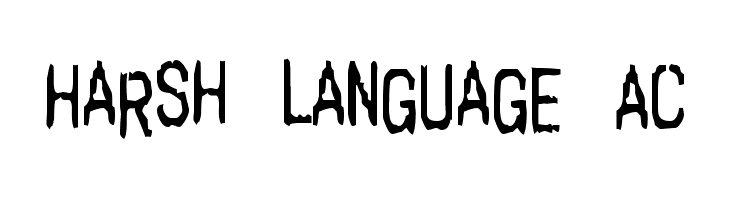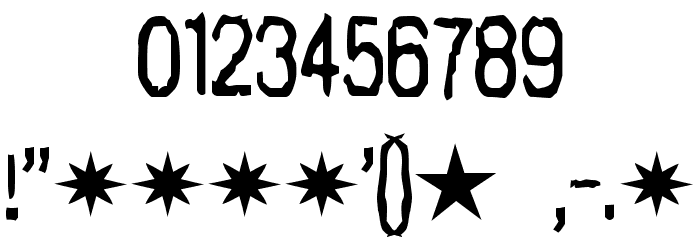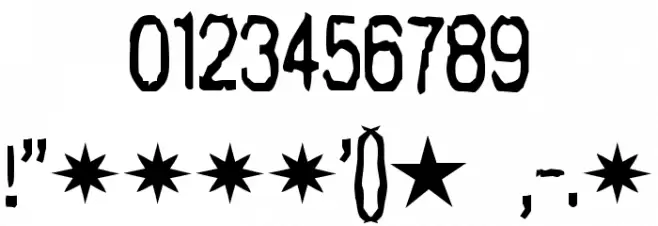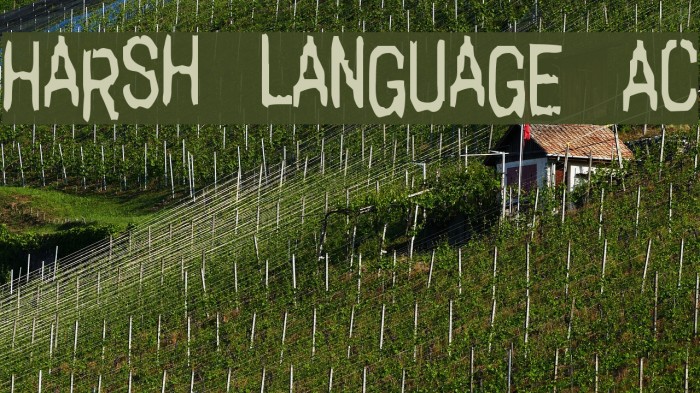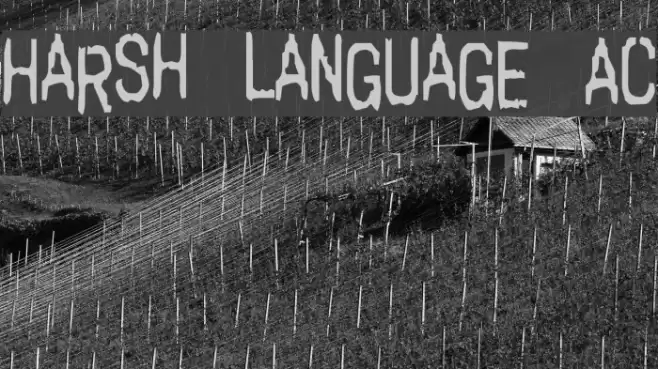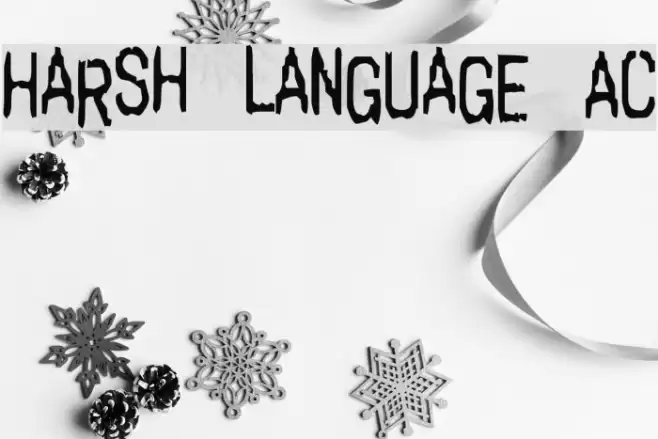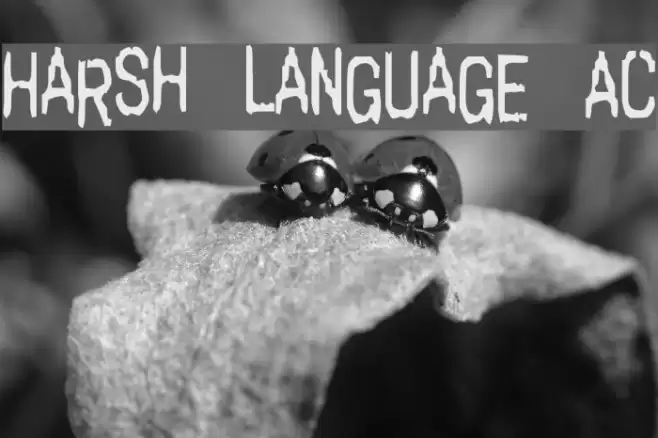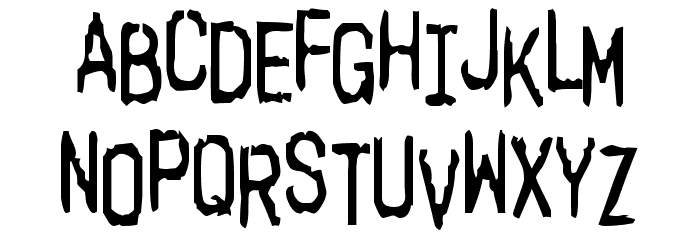
Harsh language AC Font
✎ Broken
| Projetos propostos | Ideal for album covers, posters, branding for edgy products, or any design needing a rebellious touch. |